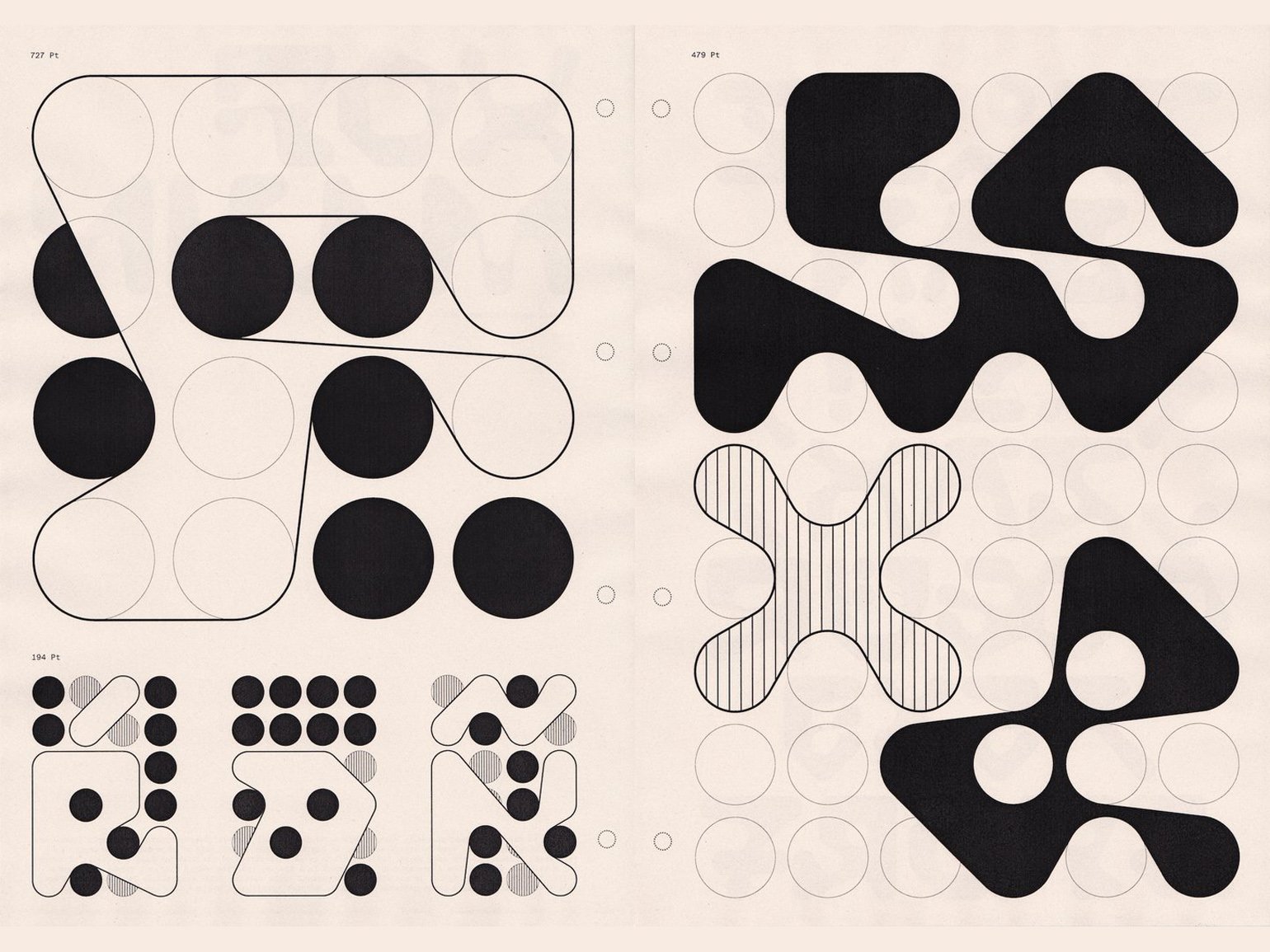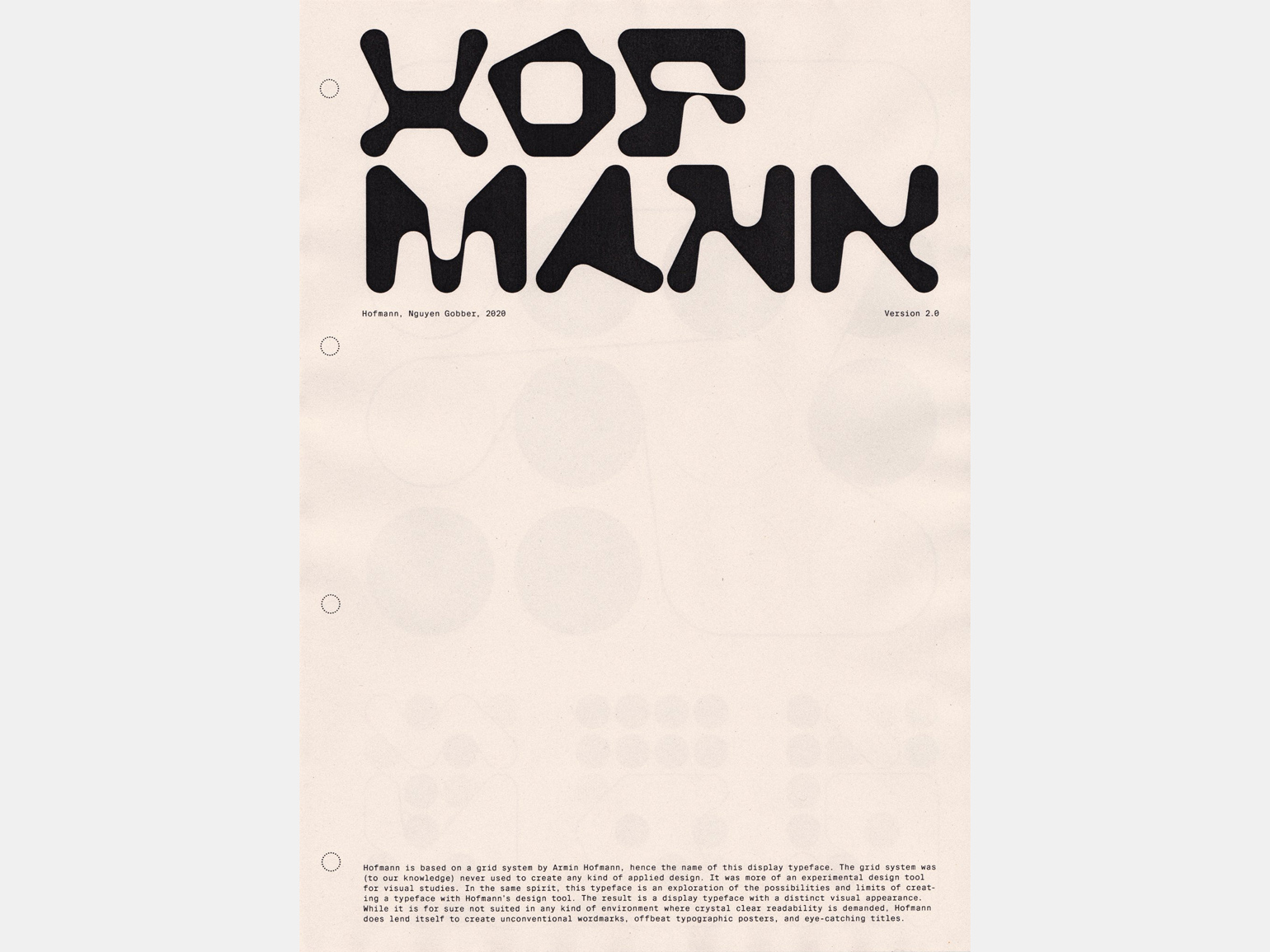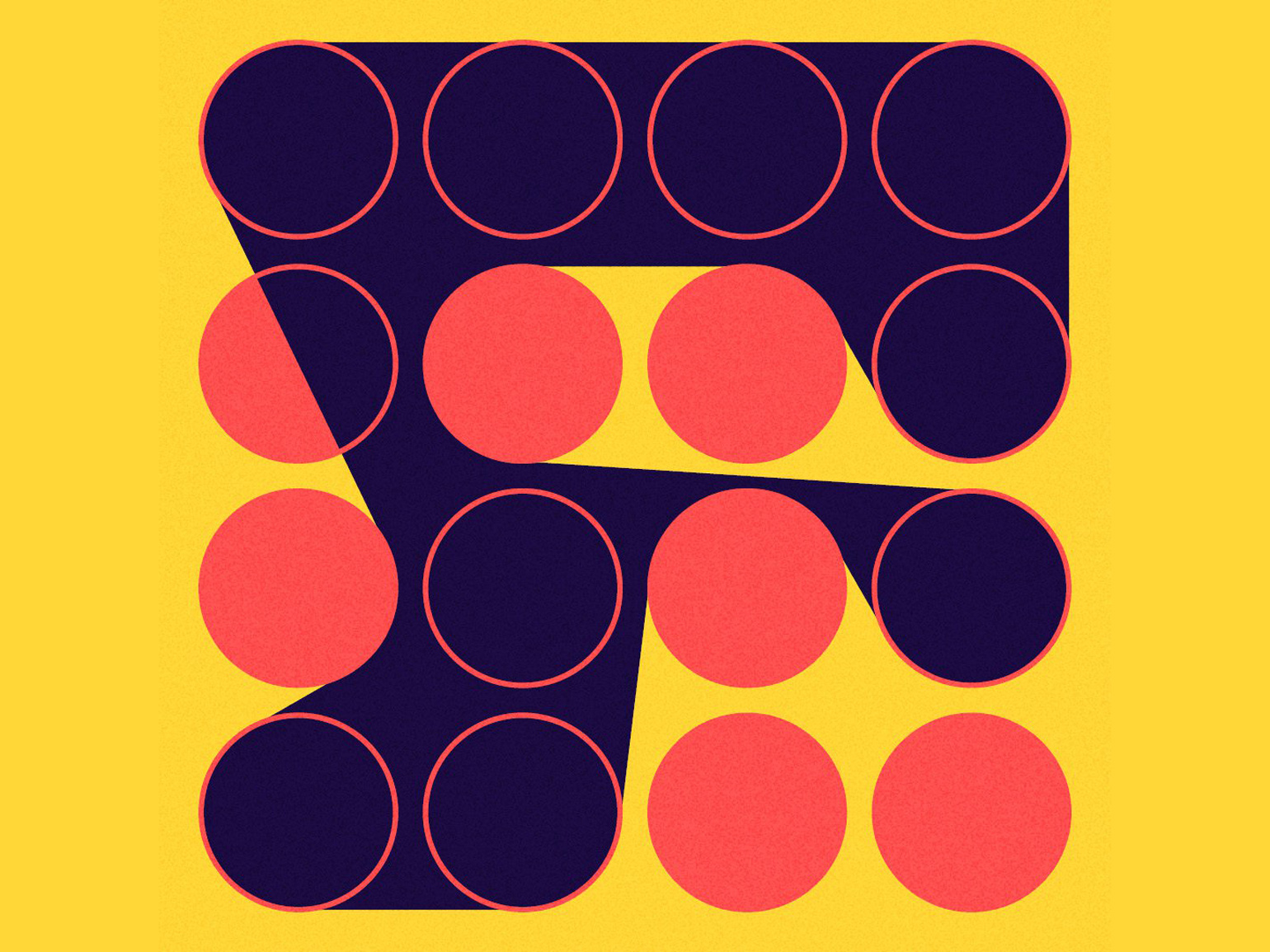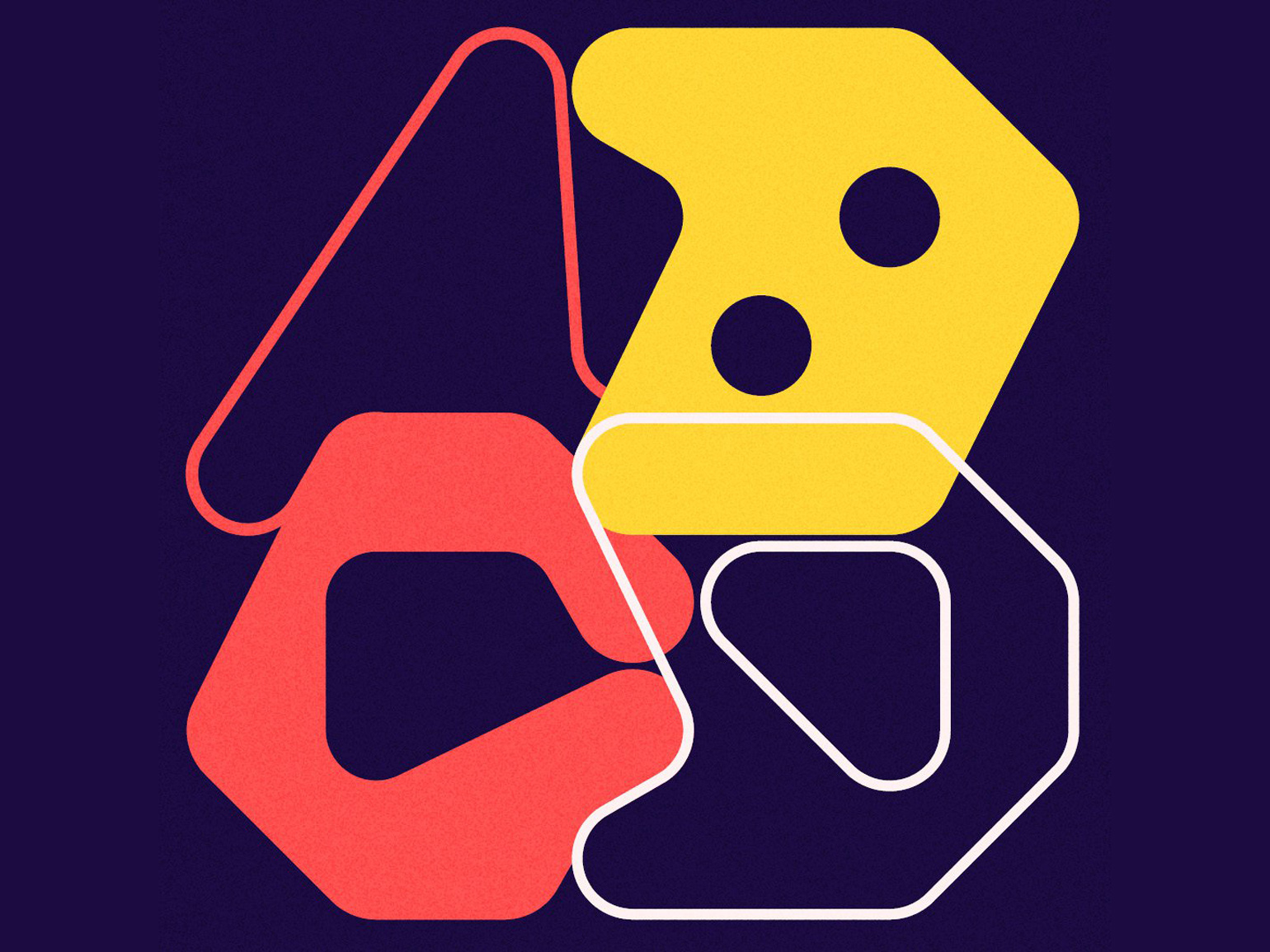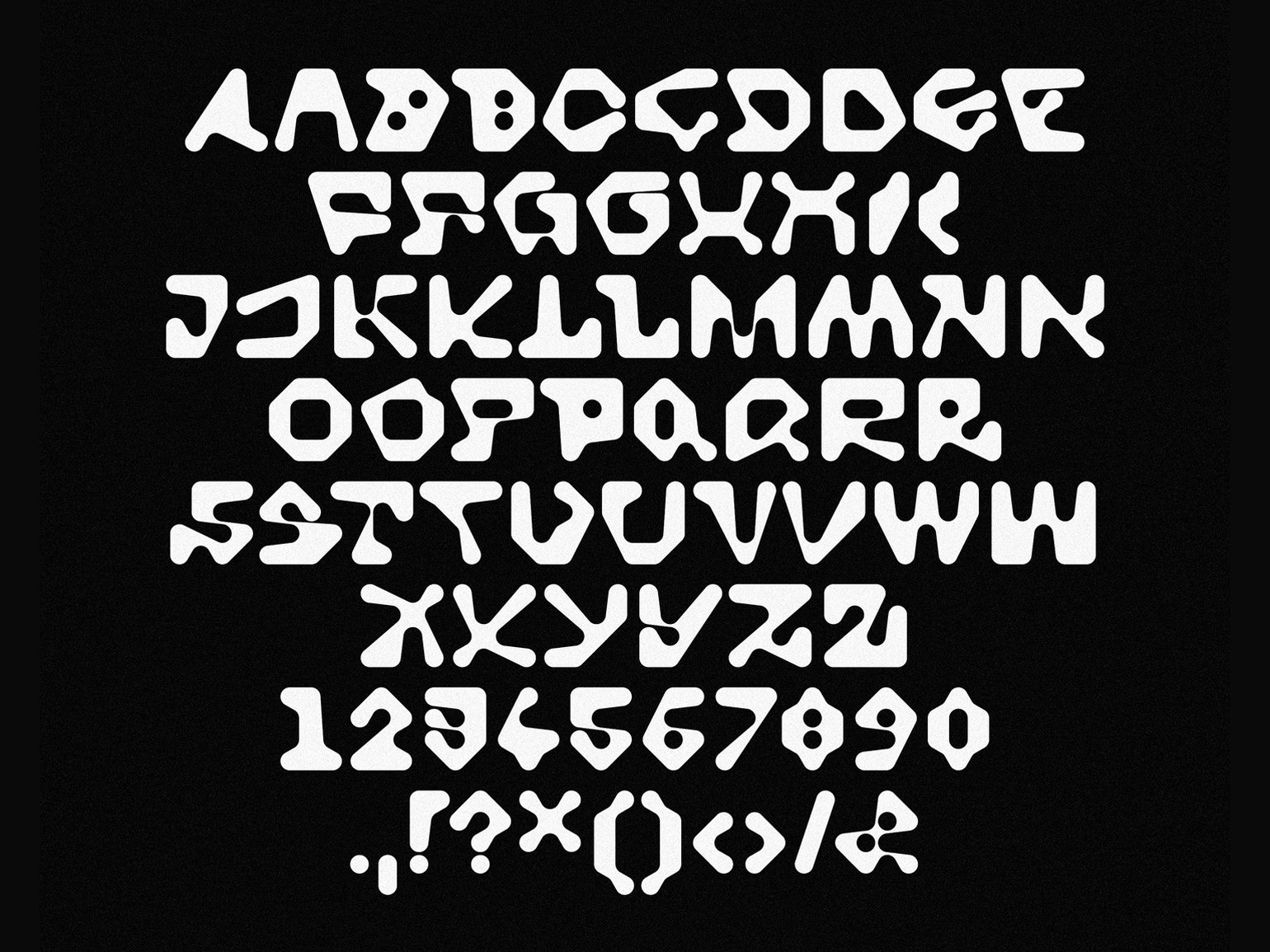
Дизайнеры сделали шрифт на основе челленджа 1960-х
За основу взяли сетку из четырёх точек.
Дизайн-студия Nguyen Gobber всегда делает обширный ресёрч перед тем, как создавать шрифт. Для своего шрифта Hofmann Хоанг Нгуен и Дэвид Гоббер погрузились в уроки и мануалы 1950-х и 1960-х годов Базельской школы дизайна.
Шрифт Hofmann
В эти годы институция стала влиятельной на международной дизайнерской сцене. ‎«Такие базельские преподаватели, как Эмиль Рудер, Армин Хофманн и Вольфганг Вейнгарт, создали особый дизайнерский подход к образованию», — говорят в студии.
Шрифт Hofmann
Ещё во время собственной учёбы Нгуен и Гоббер с удовольствием погружались в задания руководства по графическому дизайну Хофманна 1965 года.
Упражнение было частью учебного модуля по сетке. Ученикам было предложено нарисовать различные фигуры с помощью точечной сетки, при этом целью задания было не создание конкретных фигур, а исследование возможностей. Хотя это был урок с открытым результатом, пара увидела в этом возможности для создания шрифта.
Шрифт Hofmann
Каждая из букв гарнитуры построена вокруг сетки четыре на четыре, кроме широких букв, таких как M и W. В 1965-м студенты рисовали от руки, а Нгуен и Гоббер сделали шрифт цифровым, чтобы коллеги могли им пользоваться.
Шрифт Hofmann
Дизайнеры обратились к методу геометрического построения касательных между кругами. Они сделали видеоролики процесса создания глифа с пошаговым процессом рисования кругов и определения точек, а ещё с приятным моментом, когда это превращается в букву.
Шрифт Hofmann
Оглядываясь назад, дизайнеры гордятся, что создали что-то с такой строгой формулой — базовой сеткой и правилами, диктующими, как должен выглядеть каждый элемент. А ещё тем, что, несмотря на это, шрифт выглядит игривым и почти спонтанным.